Top 20 font chữ cho thương hiệu luxury: khách sạn, trang sức, thời trang cao cấp
Gợi ý 20 font thương hiệu luxury Việt hóa cho khách sạn, trang sức, thời trang cao cấp, spa premium, bao bì sản phẩm và nhận diện thương hiệu sang trọng.
Một thương hiệu luxury không chỉ sang nhờ màu đen, vàng kim hay ảnh chụp sản phẩm đắt tiền. Cảm giác cao cấp thường bắt đầu từ những chi tiết nhỏ hơn: khoảng trắng, chất liệu, tỷ lệ logo, cách dùng chữ và độ tinh tế của font. Với khách sạn, trang sức, thời trang cao cấp, spa premium hay bao bì sản phẩm, font chữ đóng vai trò như giọng nói của thương hiệu.
Nếu font quá phổ thông, thương hiệu dễ mất cảm giác riêng. Nếu font quá trang trí, thiết kế lại khó đọc và thiếu bền vững. Vì vậy, khi chọn font thương hiệu luxury, designer cần cân bằng giữa sự sang trọng, độ đọc, khả năng ứng dụng trên nhiều chất liệu và khả năng hiển thị tiếng Việt đẹp.
Danh sách dưới đây tập trung vào các font luxury Việt hóa phù hợp cho logo, bộ nhận diện, catalogue, website, bao bì, signage khách sạn, nhãn trang sức và chiến dịch thời trang.
Cách chọn font luxury cho thương hiệu cao cấp
Ưu tiên tỷ lệ chữ thanh lịch
Font luxury thường có tỷ lệ chữ đẹp, không quá chật, không quá nặng và có độ tương phản vừa đủ. Serif mảnh, display thanh lịch hoặc sans serif tối giản đều có thể tạo cảm giác cao cấp nếu tỷ lệ chữ được kiểm soát tốt.
Kiểm tra tiếng Việt trước khi làm logo
Tên thương hiệu Việt Nam thường có dấu. Nếu dấu tiếng Việt lệch, quá cao hoặc đè vào nét chữ, cảm giác cao cấp sẽ giảm ngay. Trước khi chốt font, hãy thử tên thương hiệu, tagline, địa danh khách sạn và các cụm có dấu như "trang sức", "thẩm mỹ", "khách sạn", "thời trang".
Dùng font sang nhưng không làm mọi thứ quá cầu kỳ
Luxury không đồng nghĩa với nhiều hoa văn. Một font đẹp cần khoảng trắng để thể hiện khí chất. Hãy dùng font nổi bật cho logo hoặc headline, sau đó phối với một font phụ dễ đọc cho thông tin dịch vụ, mô tả sản phẩm và nội dung website.
Top 20 font luxury Việt hóa đáng dùng
1. TH Luxury 7
TH Luxury 7 là lựa chọn rất hợp cho thương hiệu trang sức, spa cao cấp, mỹ phẩm premium và bộ nhận diện khách sạn boutique. Dáng serif sang trọng giúp logo có cảm giác tinh tế mà vẫn đủ rõ khi đặt trên bao bì hoặc bảng hiệu.
Font này nên dùng cho tên thương hiệu, headline catalogue hoặc tiêu đề landing page. Khi phối, hãy chọn sans serif mảnh cho mô tả để tổng thể không bị quá cổ điển.
2. TH Waking
TH Waking có tinh thần serif hiện đại, phù hợp với thời trang cao cấp, jewellery campaign, lookbook và thiết kế social cho brand premium. Font tạo cảm giác thanh nhưng không yếu, đủ sang để dùng trên nền ảnh sản phẩm tối giản.
Với tên thương hiệu dài, hãy thử chữ hoa và chữ thường để xem nhịp dấu tiếng Việt. TH Waking đẹp nhất khi có nhiều khoảng trắng xung quanh.
3. TH Luxury 2
TH Luxury 2 hợp với các thương hiệu muốn cảm giác classic nhưng vẫn sạch. Font có thể dùng cho logo khách sạn, menu nhà hàng fine dining, thiệp mời sự kiện private sale hoặc bao bì nước hoa.
Điểm mạnh của TH Luxury 2 là sự tiết chế. Nó không cần nhiều hiệu ứng; chỉ cần màu chữ tương phản tốt và layout thoáng là đủ tạo cảm giác cao cấp.
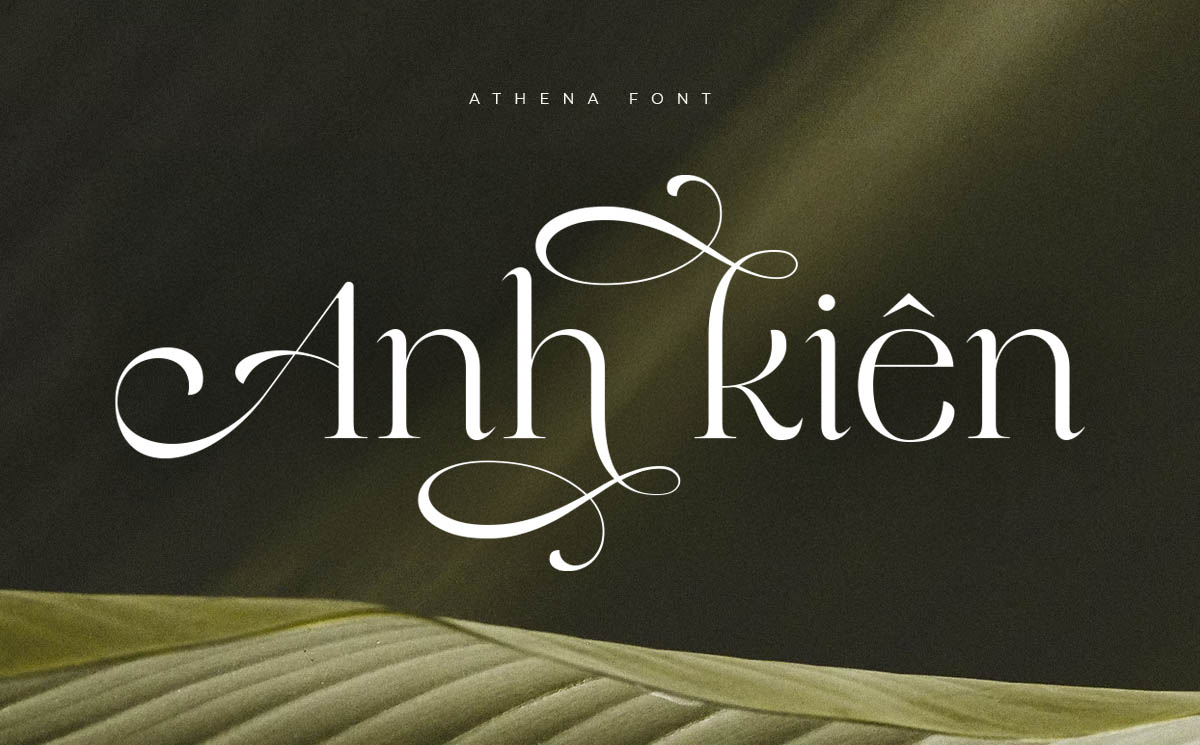
4. TH Luxury 8
Không phải luxury lúc nào cũng cần serif. TH Luxury 8 là gợi ý tốt cho khách sạn hiện đại, resort tối giản, studio kiến trúc, clinic thẩm mỹ hoặc thương hiệu lifestyle cao cấp. Dáng sans serif giúp nhận diện sạch, dễ ứng dụng trên website, app, brochure và signage.
Nếu thương hiệu của bạn hướng đến luxury hiện đại, ít trang trí và nhiều trải nghiệm số, TH Luxury 8 là lựa chọn rất đáng cân nhắc.
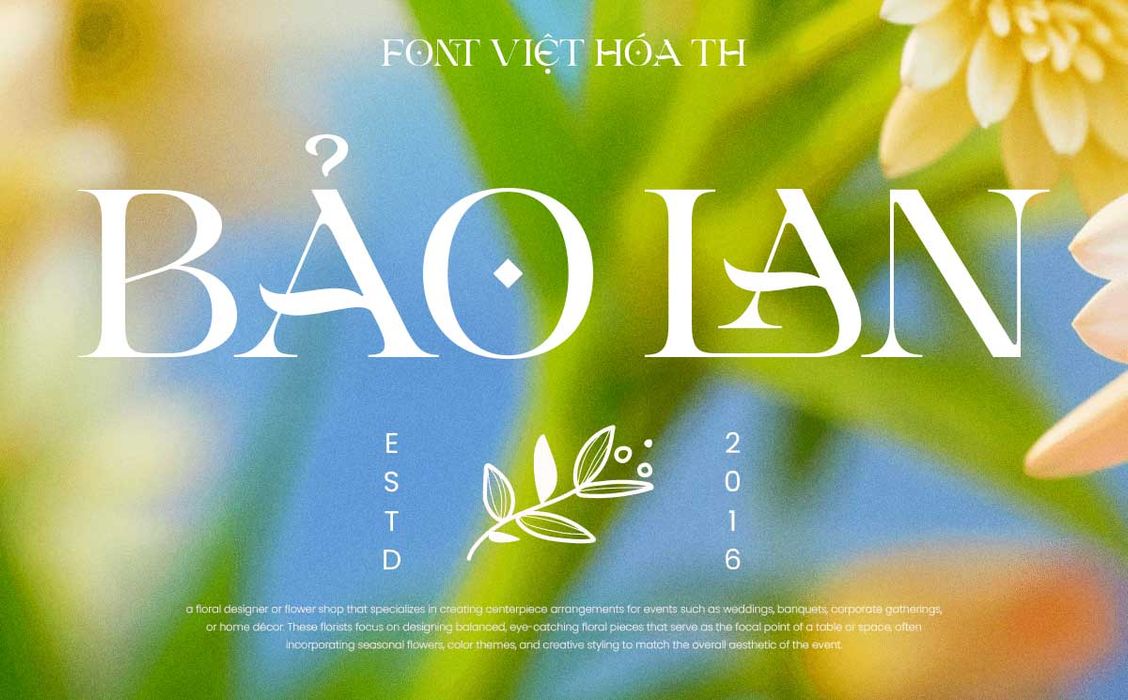
5. TH Glowen
TH Glowen hợp với thời trang cao cấp, editorial poster, lookbook, brand campaign và bao bì mỹ phẩm. Font mang cảm giác fashion rõ rệt, phù hợp khi bạn muốn chữ trở thành một phần của visual chứ không chỉ là thông tin.
Hãy dùng TH Glowen cho headline lớn, tên bộ sưu tập hoặc dòng hero. Các phần mô tả, giá và thông tin size nên dùng font phụ dễ đọc hơn.
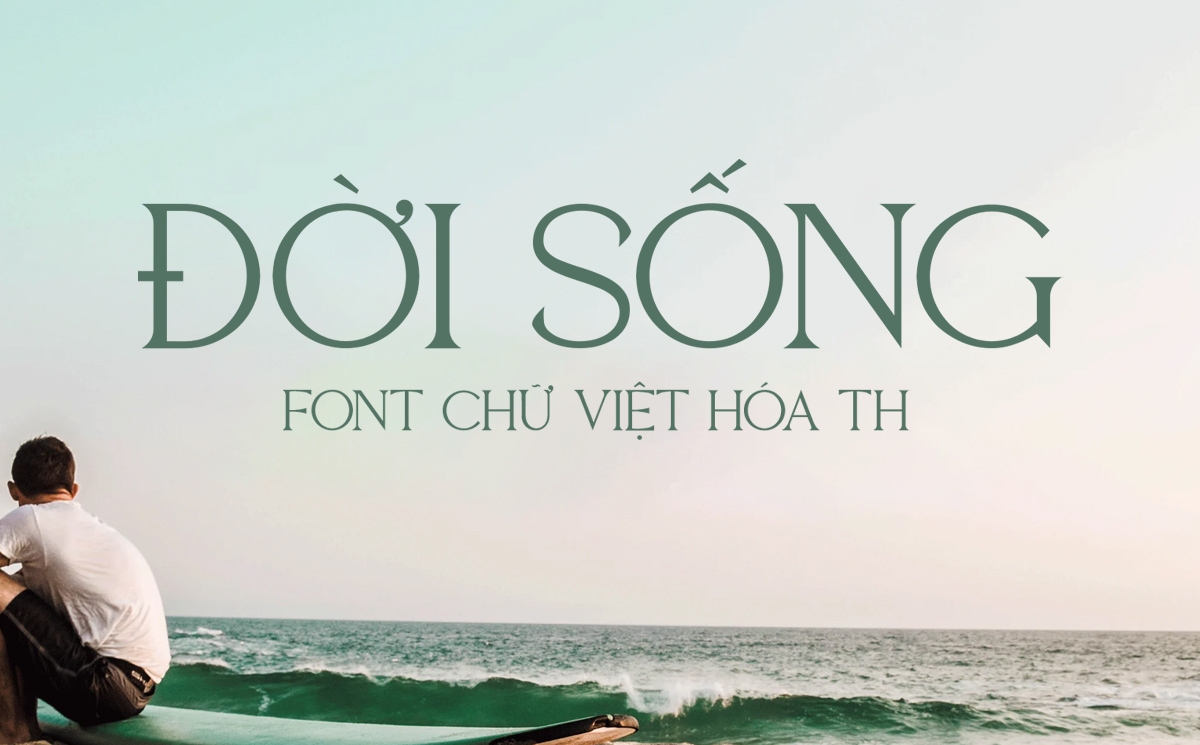
6. TH Honest Proud
TH Honest Proud tạo cảm giác sang nhưng có cá tính. Font phù hợp với thương hiệu thời trang, rượu vang, đồ da, nhãn nước hoa hoặc boutique hotel muốn có nét riêng hơn so với serif truyền thống.
Khi dùng cho logo, hãy kiểm tra khoảng cách giữa các chữ hoa. Một chút letter spacing vừa phải có thể giúp font thở tốt hơn trên bảng hiệu và nhãn sản phẩm.
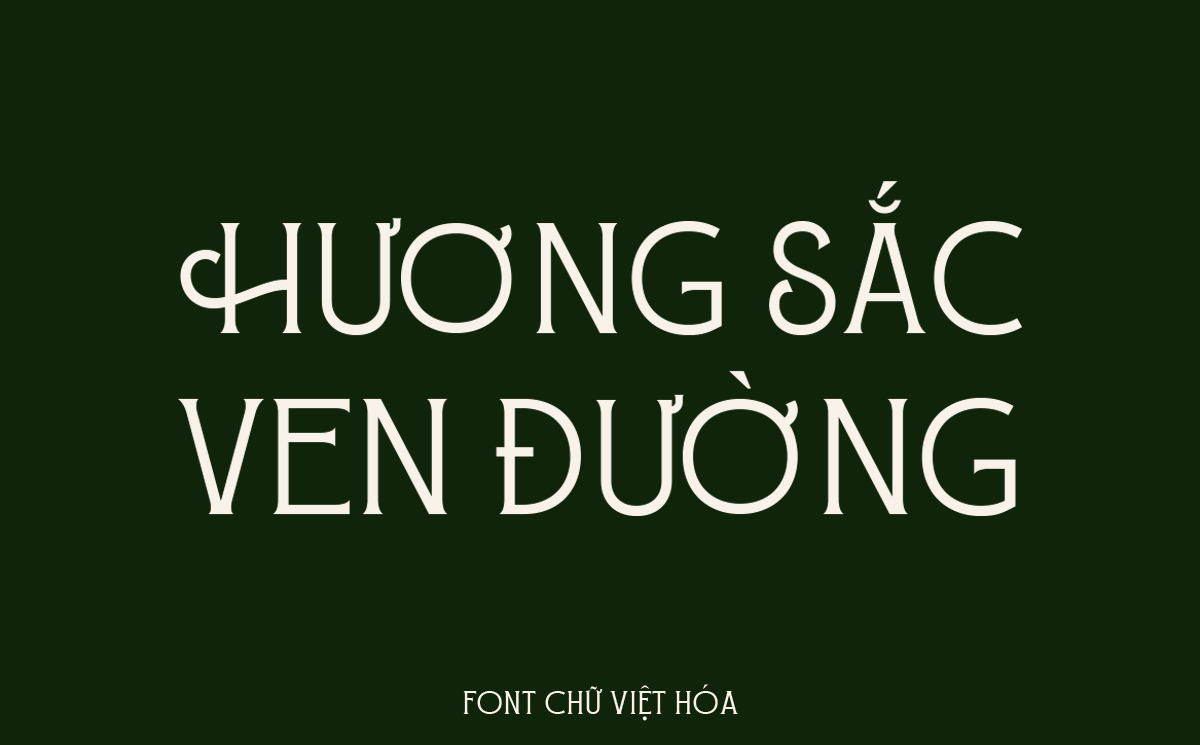
7. TH Marlino Regular
TH Marlino Regular là serif có tính ứng dụng cao cho thương hiệu luxury cần vừa đẹp vừa dễ dùng. Font hợp với catalogue sản phẩm, nhãn trang sức, brochure khách sạn, menu nhà hàng và headline website.
Đây là lựa chọn an toàn khi bạn muốn cảm giác cao cấp nhưng không muốn chữ quá phô diễn. TH Marlino Regular có thể làm font chính hoặc font phụ cho hệ thống nhận diện.
Anchor đề xuất: tải font TH Marlino Regular Việt hóa.
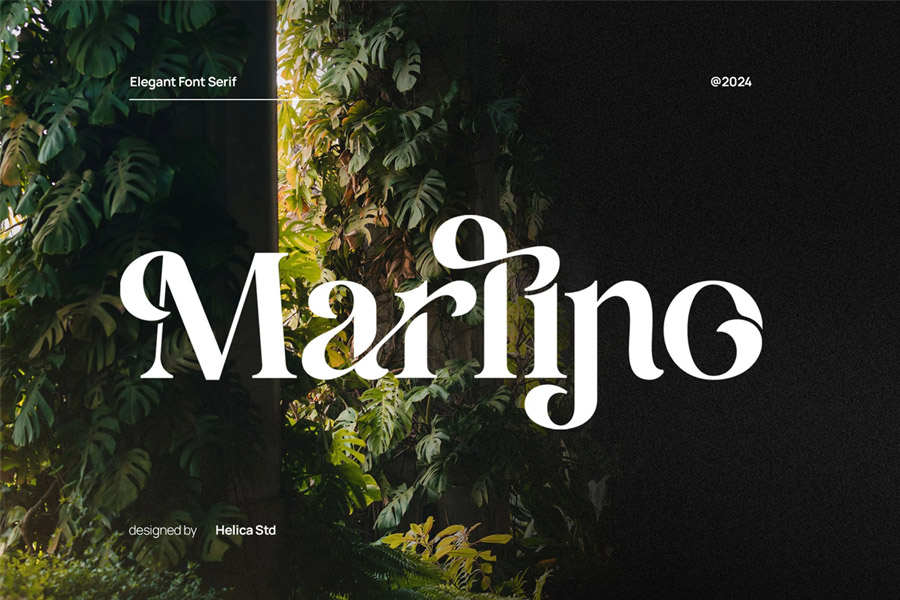
8. TH Runsling Regular
TH Runsling Regular có tinh thần thanh lịch, hiện đại và phù hợp với các thương hiệu cần sự mềm vừa đủ. Font có thể dùng cho spa cao cấp, thẩm mỹ viện, thương hiệu nội thất, khách sạn hoặc thiết kế bao bì.
Nếu dùng cho logo, hãy đặt thử trên cả nền sáng và nền tối. Font serif thanh thường đẹp nhất khi không bị che bởi texture quá mạnh.
Anchor đề xuất: tải font TH Runsling Regular Việt hóa.
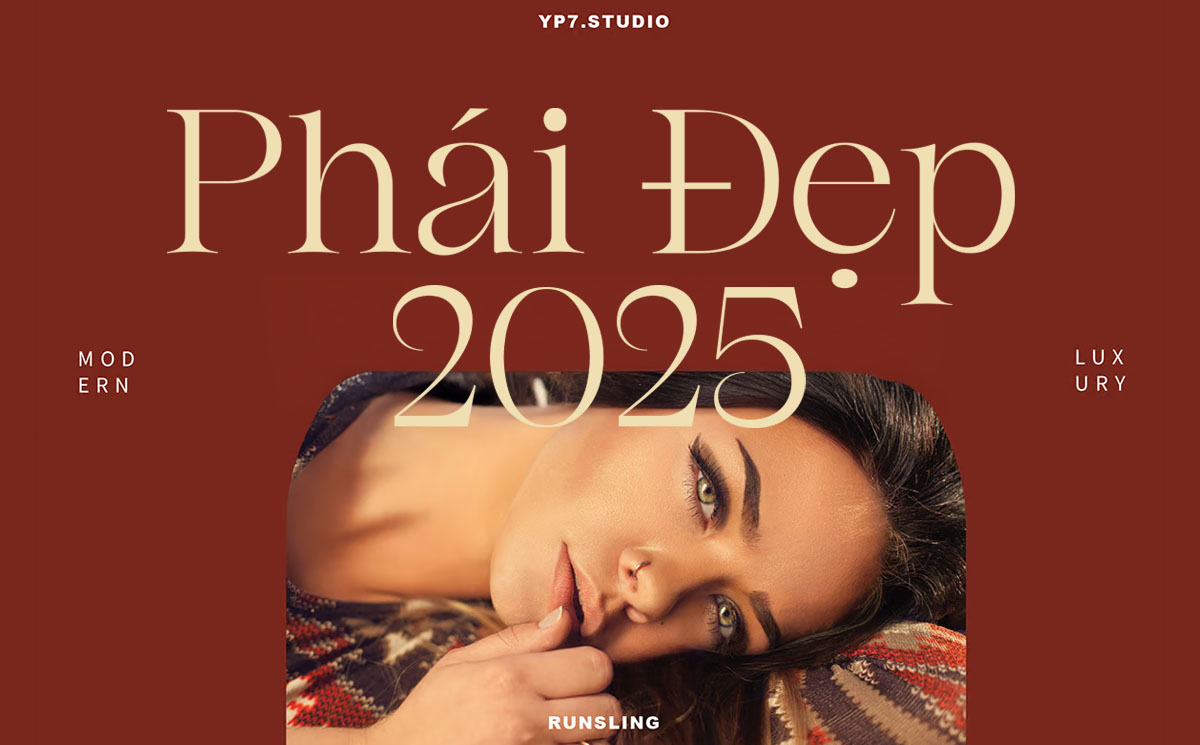
9. TH Tan Meringue
TH Tan Meringue phù hợp với luxury retro, boutique hotel, bar cao cấp, thương hiệu chocolate, nước hoa hoặc packaging có cảm giác cổ điển. Font có cá tính display, giúp thương hiệu nổi bật hơn những serif quá quen thuộc.
Nên dùng font này cho logo ngắn, tiêu đề campaign hoặc nhãn sản phẩm. Với thông tin phụ, hãy phối cùng sans serif gọn để giữ độ đọc.
Anchor đề xuất: tải font TH Tan Meringue Việt hóa.
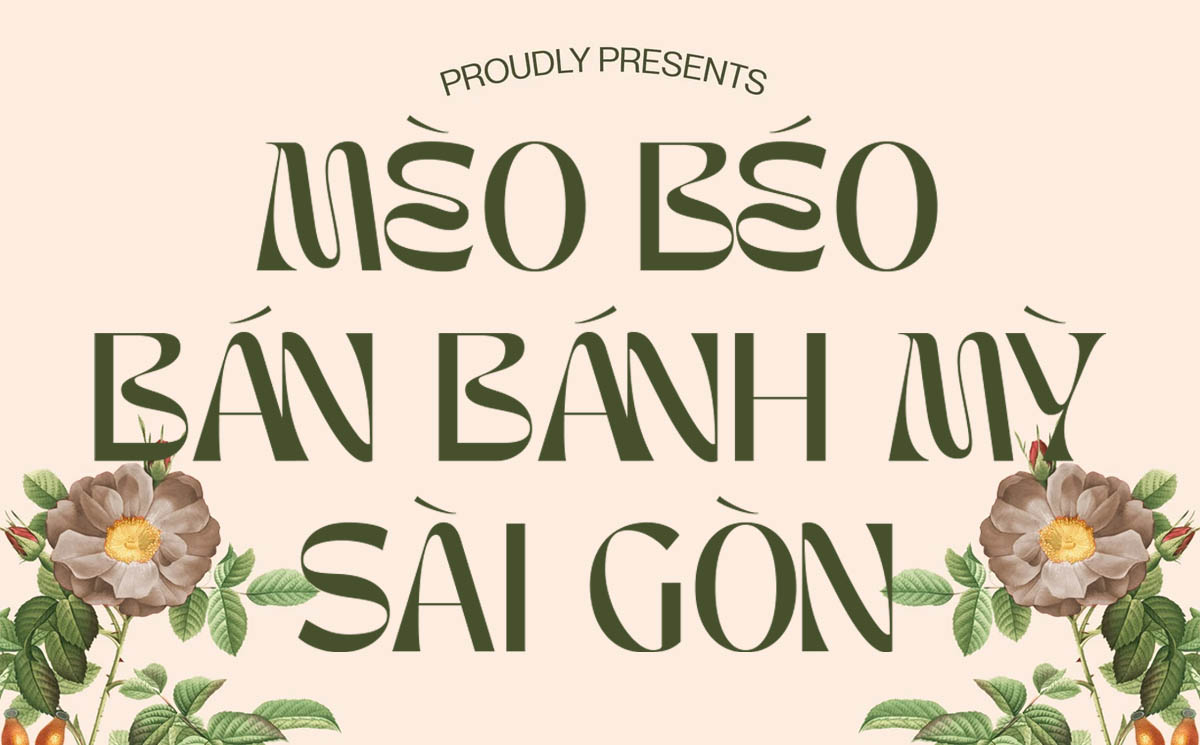
10. Morucas
Morucas có chất nghệ thuật, retro và hơi hoài cổ. Font hợp với thương hiệu hospitality có câu chuyện riêng, quán bar boutique, nhãn rượu, resort vintage hoặc bộ nhận diện sự kiện cao cấp.
Morucas nên được dùng như font điểm nhấn. Nếu dùng quá nhiều, thiết kế sẽ mất sự sang và chuyển sang cảm giác trang trí nặng.
Anchor đề xuất: tải font Morucas Việt hóa.
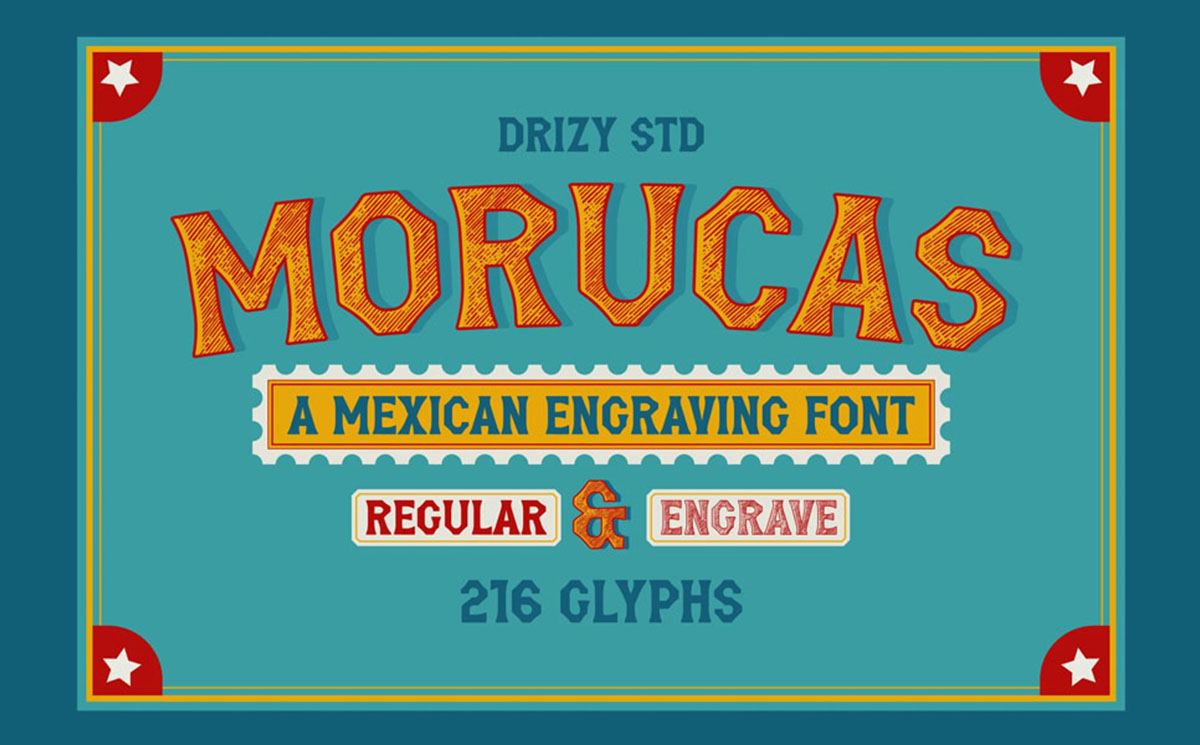
11. TH Vintage 1
TH Vintage 1 phù hợp với thương hiệu muốn khai thác cảm giác cổ điển: khách sạn di sản, nhà hàng fine dining, cigar lounge, nhãn trà, nhãn rượu hoặc packaging thủ công cao cấp.
Font này tạo cảm giác có lịch sử, nhưng vẫn cần layout tinh gọn để không bị cũ. Hãy kết hợp màu sắc trầm, giấy mỹ thuật hoặc ảnh sản phẩm có ánh sáng mềm.
Anchor đề xuất: tải font TH Vintage 1 Việt hóa.
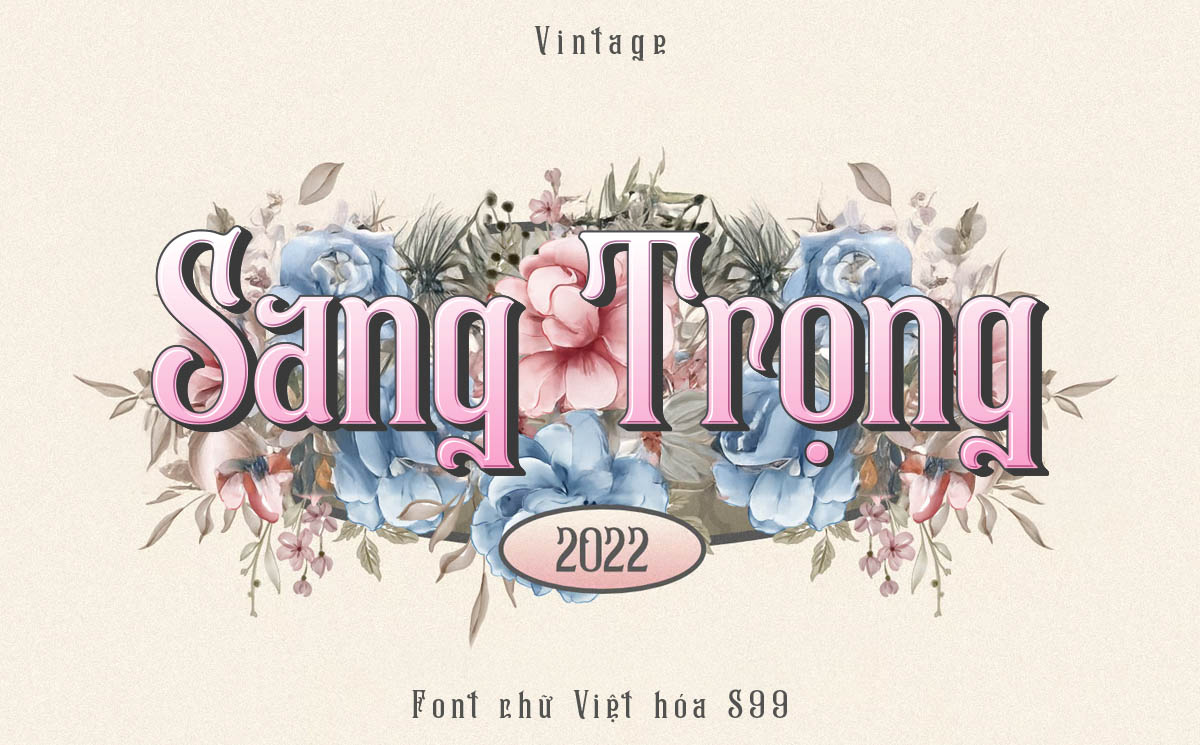
12. TH Lichsu 2
TH Lichsu 2 là lựa chọn thú vị cho luxury mang hơi hướng văn hóa, di sản hoặc boutique hotel có câu chuyện địa phương. Font có cảm giác cổ điển rõ, phù hợp với tiêu đề, biển phòng, menu hoặc nhận diện sự kiện.
Khi dùng trong thương hiệu cao cấp, nên tránh quá nhiều họa tiết đi kèm. Font đã có đủ chất cổ điển, chỉ cần bố cục sạch để giữ sự tinh tế.
Anchor đề xuất: tải font TH Lichsu 2 Việt hóa.
13. TH Kabyah
TH Kabyah hợp với các concept luxury Á Đông, khách sạn boutique, spa trị liệu, trà đạo, nhà hàng cao cấp hoặc thương hiệu khai thác cảm hứng cổ trang. Font có tính văn hóa mạnh nên cần dùng đúng ngữ cảnh.
Nếu dùng cho logo, nên giữ tên thương hiệu ngắn và bố cục rộng. Với đoạn mô tả dài, hãy chuyển sang font phụ trung tính.
Anchor đề xuất: tải font TH Kabyah Việt hóa.
14. TH Chrone
TH Chrone không mềm như các serif luxury, nhưng lại hợp với thương hiệu cao cấp cần sự mạnh mẽ: thời trang nam, đồng hồ, đồ da, kiến trúc, nội thất hoặc khách sạn có phong cách masculine.
Font nên dùng cho headline, nhãn sản phẩm hoặc logo ngắn. Khi phối với serif mảnh, TH Chrone có thể tạo hệ nhận diện vừa chắc vừa sang.
Anchor đề xuất: tải font TH Chrone Việt hóa.
15. TH Dark Sincity
TH Dark Sincity phù hợp với luxury cá tính: fashion editorial, thương hiệu nightlife, boutique bar, nước hoa niche hoặc campaign cần cảm giác bí ẩn. Font tạo ấn tượng mạnh hơn các serif an toàn.
Hãy dùng TH Dark Sincity cho tiêu đề ngắn, không nên dùng cho nội dung mô tả dài. Một nền tối, ánh sáng tương phản và khoảng trắng tốt sẽ giúp font này phát huy hiệu quả.
Anchor đề xuất: tải font TH Dark Sincity Việt hóa.
16. TH Midnight Romance
TH Midnight Romance hợp với luxury gothic, nước hoa, trang sức bạc, thời trang đêm hoặc bộ sưu tập có tinh thần bí ẩn. Font có cảm giác huyền bí nhưng vẫn có thể giữ được sự thanh lịch nếu dùng tiết chế.
Nên dùng font này cho tên campaign, dòng collection hoặc logo phụ. Với brand khách sạn truyền thống, hãy cân nhắc kỹ vì sắc thái gothic có thể hơi mạnh.
Anchor đề xuất: tải font TH Midnight Romance Việt hóa.
17. TH Qultures
TH Qultures có chất gothic cổ điển, phù hợp với thời trang concept, packaging đặc biệt, nhãn rượu, sự kiện cao cấp hoặc thương hiệu muốn tạo cảm giác quyền lực. Đây là font nên dùng như một điểm nhấn hơn là font hệ thống.
Nếu chọn TH Qultures, hãy giữ bảng màu và hình ảnh thật tinh gọn để font không làm thiết kế trở nên nặng.
Anchor đề xuất: tải font TH Qultures Việt hóa.
18. TH Raboan
TH Raboan phù hợp với thương hiệu thời trang hoặc mỹ phẩm lấy cảm hứng Hàn Quốc. Font tạo cảm giác khác biệt, hiện đại và có tính nhận diện cao, đặc biệt hợp với brand trẻ nhưng vẫn muốn giữ sự chỉn chu.
Với luxury Hàn Quốc, hãy phối TH Raboan cùng layout tối giản, nhiều khoảng trắng và ảnh sản phẩm sạch để tránh cảm giác quá vui mắt.
Anchor đề xuất: tải font TH Raboan Việt hóa.
19. TH Busan Garden
TH Busan Garden có tinh thần Hàn Quốc mềm hơn, hợp với beauty brand, thời trang nữ, café boutique, spa hoặc lifestyle cao cấp. Font tạo cảm giác khác biệt mà không quá nặng như gothic hay retro.
Nếu dùng cho logo, hãy thử cả chữ hoa và chữ thường để chọn nhịp phù hợp. Font này hợp với bảng màu nhẹ, ảnh sản phẩm sáng và bố cục sạch.
Anchor đề xuất: tải font TH Busan Garden Việt hóa.
20. BL Ample
BL Ample không phải serif truyền thống, nhưng rất hợp với luxury hiện đại trong lĩnh vực khách sạn công nghệ, kiến trúc, nội thất, showroom xe, thiết bị cao cấp hoặc thương hiệu lifestyle mang tinh thần tương lai. Font tạo cảm giác chắc, sạch và có tính hệ thống.
Khi dùng BL Ample trong brand cao cấp, hãy tiết chế màu sắc và hiệu ứng. Sự sang trọng của sans serif hiện đại thường đến từ tỷ lệ, khoảng trắng và chất liệu hơn là trang trí.
Anchor đề xuất: tải bộ font BL Ample Việt hóa.
Gợi ý chọn font theo ngành
Khách sạn và resort cao cấp: Khách sạn, resort và nhà hàng fine dining nên ưu tiên font có độ đọc tốt ở nhiều kích thước. TH Luxury 2, TH Marlino Regular, TH Runsling Regular và TH Luxury 8 là các lựa chọn dễ triển khai cho signage, menu, website và tài liệu in.
Trang sức và nước hoa: Trang sức, nước hoa và mỹ phẩm premium cần cảm giác tinh tế, mảnh và giàu khoảng trắng. TH Luxury 7, TH Waking, TH Glowen hoặc TH Honest Proud sẽ phù hợp cho logo, nhãn hộp, catalogue và visual campaign.
Thời trang cao cấp: Thời trang có thể mạnh tay hơn với font display. TH Glowen, TH Dark Sincity, TH Midnight Romance, TH Qultures hoặc TH Tan Meringue sẽ tạo cá tính rõ cho collection, lookbook và poster.
Lưu ý khi triển khai font luxury vào nhận diện
Đừng chỉ thử font trên một poster đẹp. Hãy đặt font vào toàn bộ hệ thống: logo, tagline, menu, bảng hiệu, bao bì, website, bài social, hóa đơn, voucher và tài liệu bán hàng. Một font luxury tốt phải đẹp ở headline nhưng vẫn không làm hệ thống nhận diện trở nên khó vận hành.
Với thương hiệu có tiếng Việt, hãy kiểm tra dấu trên mọi chất liệu. Dấu tiếng Việt trên ép kim, dập nổi, mica, vải hoặc màn hình LED có thể khác nhiều so với bản xem trên máy tính. Nếu font quá mảnh, cần tăng kích thước hoặc chọn chất liệu in phù hợp.
Font thương hiệu luxury cần vừa đẹp, vừa có khả năng ứng dụng lâu dài. Nếu bạn muốn cảm giác thanh lịch an toàn, hãy bắt đầu với TH Luxury 7, TH Waking, TH Luxury 2 hoặc TH Marlino Regular. Nếu cần luxury hiện đại, TH Luxury 8 và BL Ample là hướng đáng thử. Nếu thương hiệu thời trang cần cá tính mạnh, TH Glowen, TH Dark Sincity, TH Midnight Romance hoặc TH Qultures sẽ tạo dấu ấn rõ hơn.
Điều quan trọng nhất là chọn font theo chiến lược thương hiệu, không chỉ theo cảm giác "đẹp mắt" ở một ảnh preview. Font đúng sẽ giúp thương hiệu cao cấp trông nhất quán, tinh tế và đáng tin hơn ở mọi điểm chạm.